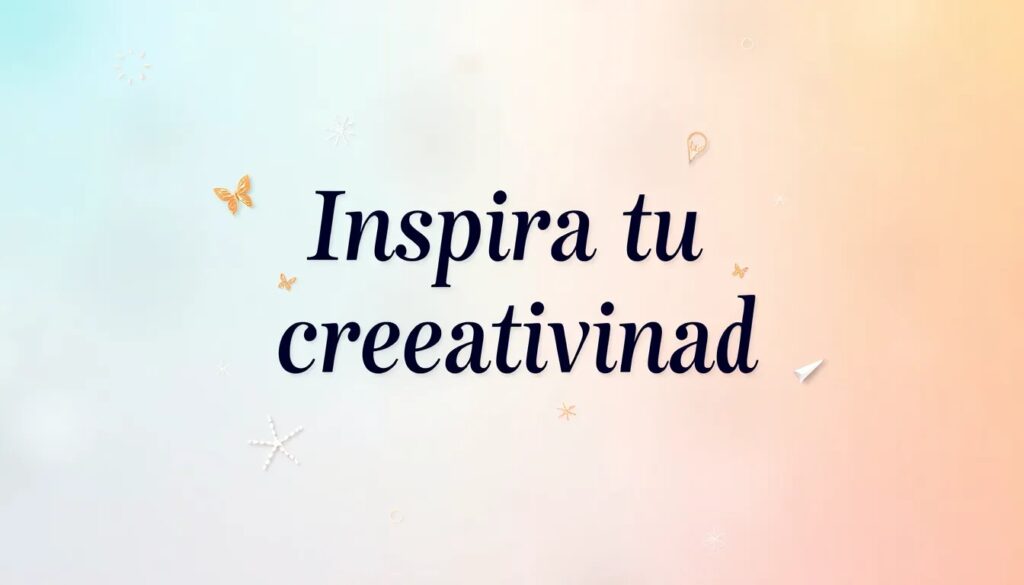
Instagram tipografía: las mejores fuentes para tus publicaciones
La instagram tipografía se ha convertido en un elemento clave para destacar en esta popular red social. La forma en que presentas tu contenido puede marcar la diferencia en la interacción con tus seguidores. En este artículo, exploraremos las mejores fuentes y estilos que puedes utilizar para hacer que tus publicaciones sean más atractivas y memorables.
Con la creciente competencia en Instagram, es fundamental que encuentres maneras creativas de captar la atención de tu audiencia. A través del uso de diferentes tipografías, puedes realzar tus mensajes y dar un toque único a tus publicaciones.
¿Qué es la instagram tipografía y por qué es importante?
La instagram tipografía se refiere a la selección de fuentes y estilos de letra que utilizas en tus publicaciones de Instagram. Es importante porque puede influir en la percepción de tu marca y en la forma en que los usuarios interactúan con tu contenido. Una tipografía bien elegida puede transmitir emociones y captar la atención de manera efectiva.
Además, el uso de tipografías creativas puede ayudarte a diferenciarte en un mar de publicaciones similares. La elección de la fuente adecuada puede comunicar tu personalidad y estilo, creando una conexión más fuerte con tu audiencia.
De hecho, muchas marcas han encontrado en la tipografía una herramienta poderosa para establecer su identidad visual. Con una buena tipografía, tus publicaciones pueden ser más memorables y aumentar la retención de información entre tus seguidores.
¿Cómo funciona el conversor de letras para Instagram?
Los conversores de letras para Instagram son herramientas en línea que te permiten transformar texto simple en diferentes estilos tipográficos. Estas herramientas son muy útiles para los usuarios que desean añadir un toque especial a sus publicaciones sin complicaciones. Al ingresar tu texto, puedes elegir entre múltiples estilos y ver los resultados en tiempo real.
Estas aplicaciones utilizan caracteres Unicode para generar letras con diferentes efectos, como negritas, cursivas o incluso estilos más ornamentales. Esto significa que puedes jugar con la presentación de tus mensajes y hacerlos más atractivos visualmente.
- Interfaz sencilla y fácil de usar.
- Variedad de estilos que puedes aplicar.
- Compatibilidad con diferentes plataformas sociales.
- Posibilidad de copiar y pegar directamente en Instagram.
Además, muchos de estos convertidores te permiten combinar el texto con emojis y otros símbolos, lo que te brinda aún más opciones para personalizar tus publicaciones y hacerlas destacar.
¿Cuáles son las mejores fuentes para Instagram?
Cuando se trata de elegir fuentes para tus publicaciones en Instagram, hay varias opciones que destacan por su popularidad y atractivo. Algunas de las mejores fuentes incluyen:
- Helvetica: Clásica y muy legible, perfecta para mensajes directos.
- Pacifico: Una fuente cursiva que otorga un toque más informal y amigable.
- Impact: Ideal para títulos y frases que necesitas que resalten.
- Amatic SC: Con un estilo manuscrito, ideal para dar un toque personal.
- Roboto: Moderna y versátil, se adapta a diferentes tipos de contenido.
La elección de la fuente dependerá de la imagen que deseas proyectar y del mensaje que pretendes comunicar. Asegúrate de que la fuente elegida sea legible y se alinee con la estética de tu perfil.
¿Dónde encontrar letras bonitas para copiar y pegar en Instagram?
Existen múltiples recursos donde puedes encontrar letras bonitas para Instagram. Algunos de los más populares incluyen:
- Glyphy: Un conversor de letras que ofrece más de 299 fuentes para elegir.
- CoolText: Generador de logotipos y textos estilizados.
- Fancy Text Generator: Permite crear textos decorativos con un solo clic.
- Instagram Fonts: Herramienta específicamente diseñada para generar fuentes compatibles con Instagram.
Estas herramientas son ideales para quienes buscan personalizar su biografía o publicaciones, facilitando la creación de contenido atractivo sin necesidad de habilidad de diseño.